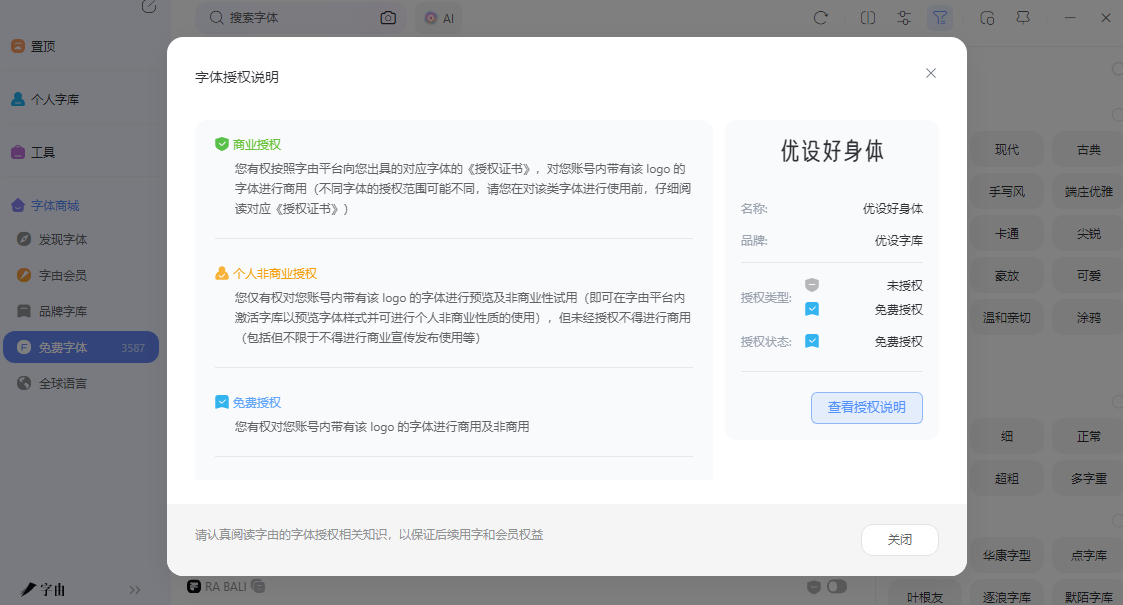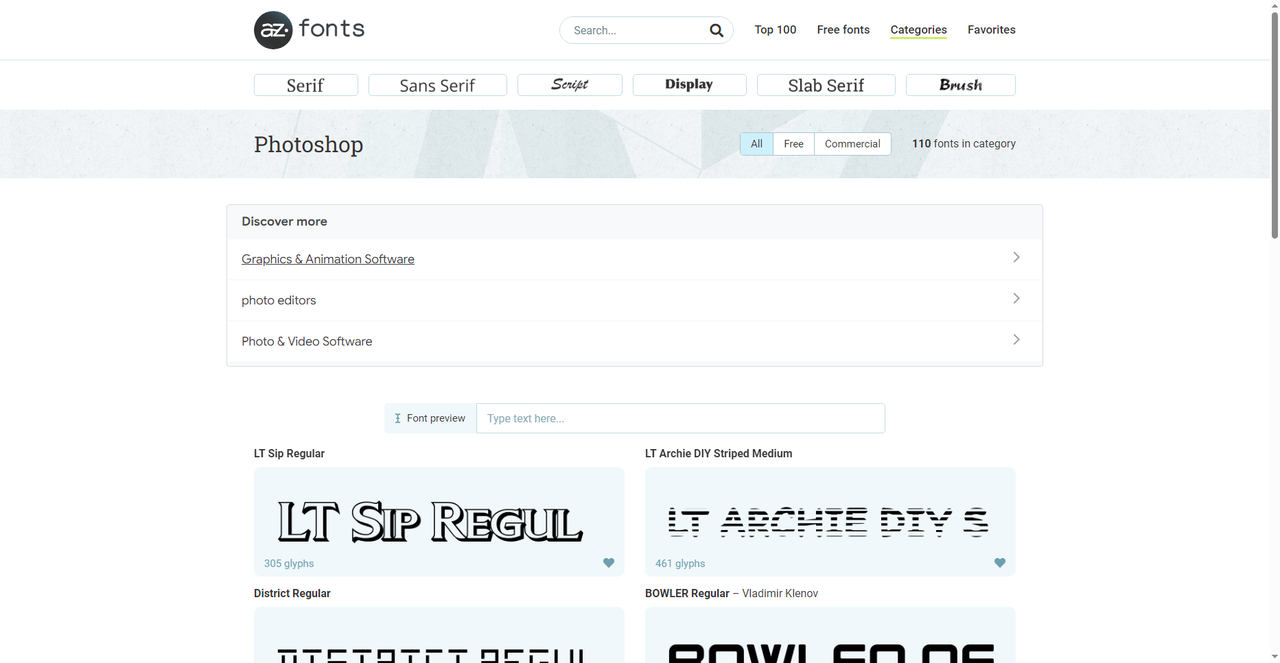
PS英文字体哪里找?这5个网站免费下载又好看
打开Photoshop的字体下拉菜单,你是不是也这样:看到Arial和Times New Roman总觉得太老气;Helvetica的话又不够个性。翻来覆去就那几款系统默认字体,做出来的海报、Logo、封面,总感觉跟别人的差不多。其实不是PS不行,是你的字体库内容太少了。网上有很多专门给设计师准备的英文字体网站,免费、可商用、风格多样,下载后直接装进PS里用。今天我就整理了5 个靠谱的英文字体资源站,从免安装激活到一键下载,覆盖了不同使用习惯。
字由它和其他字体下载站最大的区别是:你不需要下载任何字体文件。打开字由客户端,里面收录了上万款字体,其中英文字体占了很大比重。找到想要的英文字体,点一下“激活”,它立刻出现在PS的字体列表里,不用重启软件,不用打开系统字体文件夹。
字由的筛选功能做得很细。左侧筛选栏里,在“字体语言”下勾选“英文(拉丁)”,所有英文字体会一次性列出来。然后你可以继续按“字体类型”筛选:衬线体、无衬线体、手写体、展示体、等宽体……每种风格下面又有几十到上百款具体字体。
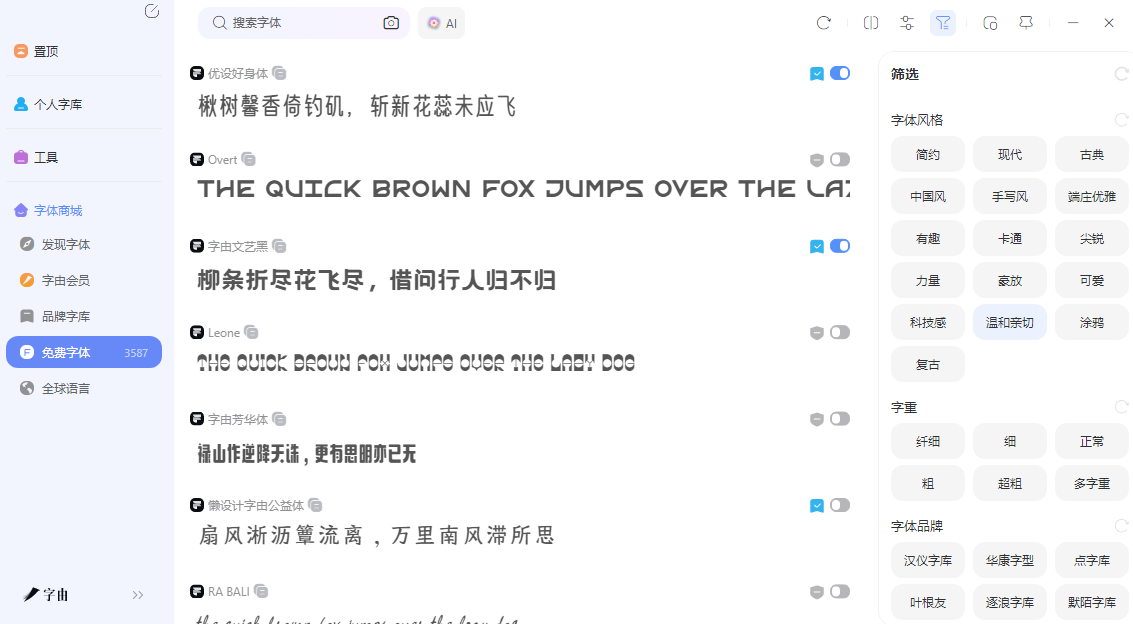
比如你想找一款适合做海报标题的粗体英文字体,勾选“英文”+“展示体”+“免费商用”,系统会把你需要的所有字体列出来,每款都有预览图,输入你自己的文案实时看效果。找到喜欢的,点一下“激活”,打开PS,在字体下拉菜单里就能看到它。因为字由的“激活”机制太适合PS了。不喜欢的点“取消激活”,字体就从PS列表里消失,不占系统空间。
就算换了设备也不用怕,字由的个人云字库可以把你激活过的字体、收藏的字体自动同步到云端。你在公司电脑上激活了一堆英文字体,晚上回家打开笔记本,登录同一个字由账号,PS里那些字体全都在,不用重新找重新激活。而且字由支持Windows和macOS,不管你是用PC还是Mac版PS,字体库始终一致。
2、fonts
第二个网站就叫fonts。这个站有个很实用的功能:它专门做了一个“Photoshop”分类标签。截图显示,在分类筛选里直接有“Photoshop”选项,点进去能看到110款适合在PS中使用的英文字体。为什么这些字体被标记为“Photoshop”?可能是因为它们多为OpenType格式,支持PS的高级排版功能(如连字、替代字符等),或者本身就是设计师在做PS项目时高频使用的款式。这个分类帮PS用户省去了“下载一堆字体然后发现不适合”的试错成本。这个站上的字体授权类型混合,下载前需要看页面标注。但“Photoshop”分类下的字体大多是免费或免费商用的,适合PS用户直接下载安装。
3、FreeFontsVault
第三个网站是FreeFontsVault。这是一个老牌的免费字体资源站,首页展示了最新推荐的免费字体,比如“Grad Theft Auto V”“SKIBIDI”“TOILET”“FF Trixie Font”“Corleone Font”“GTA 6 Logo Font”“Skibidi Toilet Font”等。
比如你要做一个复古风的Logo,点“Vintage”标签;要做海报标题,点“display”或“headline”;要搭配品牌VI,点“elegant font”或“clean font”。每个标签下都有大量免费字体,全部支持免费下载。网站还提供了搜索框,可以按字体名称直接搜。FreeFontsVault上的字体授权大多是免费个人使用,部分标注免费商用。下载前建议看一下字体详情页的说明。如果你是一个喜欢“逛”字体站、按风格翻找的设计师,这个站的标签系统会让你很顺手。
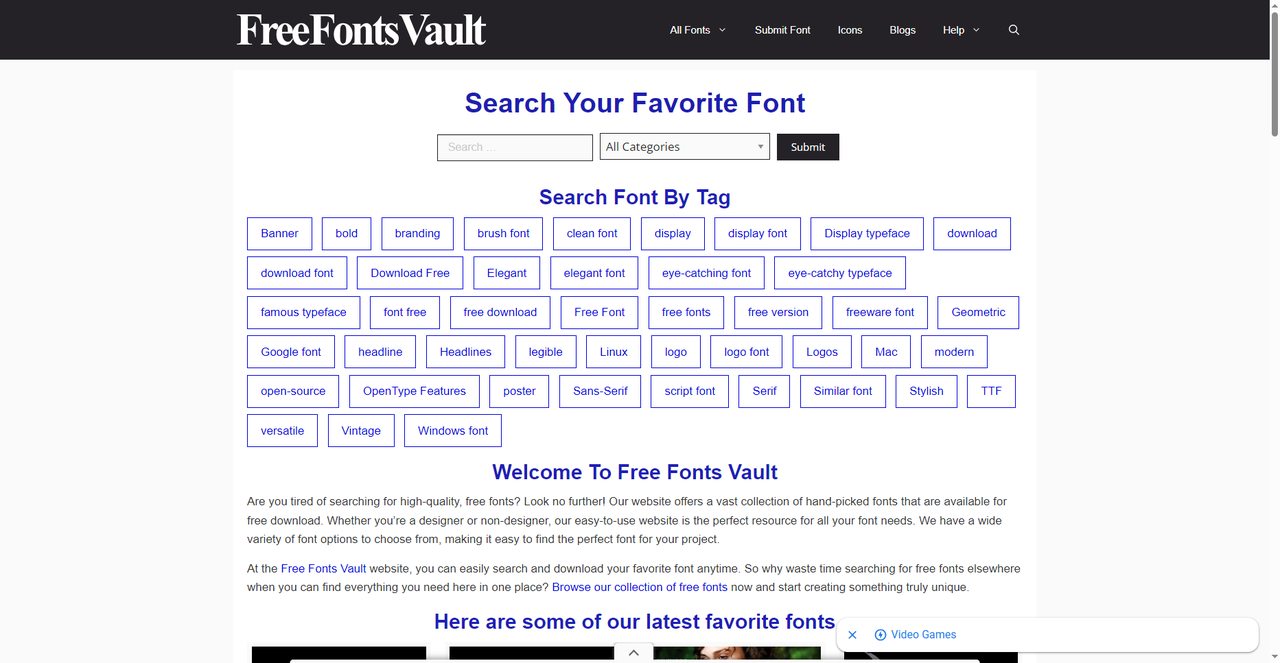
4、fontbolt
第四个网站是fontbolt。这个站的定位很特别——它专门收集电影、游戏、音乐、书籍相关的主题英文字体。如果你正在做一张电影主题的海报,或者要给一款游戏设计Logo,或者想模仿某部经典电影的片名字体,fontbolt是最快的资源站。它收集了大量基于流行文化IP的字体复刻版,比如《侠盗猎车手》字体、《星球大战》字体等。这些字体大多是粉丝复刻的免费版本,适用于个人项目,商用需要谨慎确认授权。fontbolt的字体下载通常直接提供TTF文件,下载后双击安装就能在PS里用。适合做娱乐向、流行文化向的设计项目。
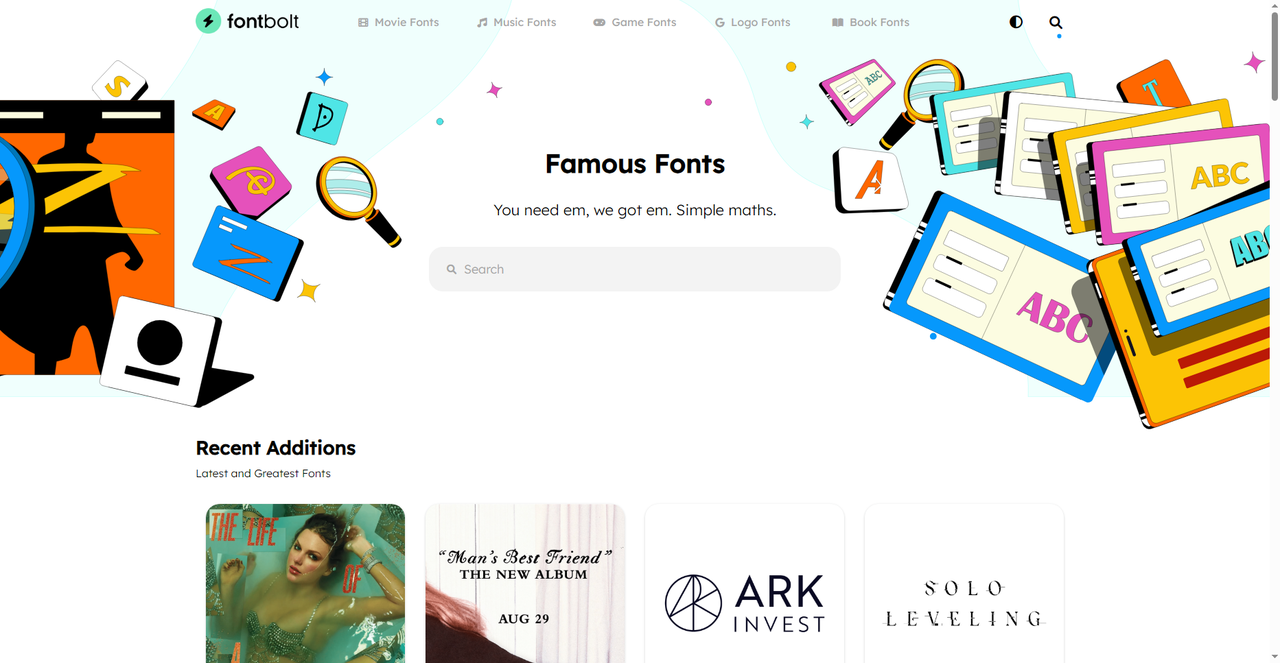
5、Adobe Fonts
第五个工具是Adobe Fonts。它不是独立的网站,而是Adobe Creative Cloud订阅的一部分。只要你订阅了PS、AI等Adobe软件,就可以免费使用Adobe Fonts里的上千款专业字体。Adobe Fonts的优势在于:字体直接同步到你的Adobe软件里。在PS里打开“字体”菜单,点击“从Adobe Fonts添加字体”,浏览网页,点击“激活”字体,它立刻出现在PS的字体列表中,不需要下载、安装。和字由的激活机制类似,但只限于Adobe生态。如果你已经是Creative Cloud用户,Adobe Fonts是你最方便的选择。它收录的字体都是专业字体公司出品,质量极高,且全部授权用于商业项目(只要你的订阅有效)。缺点是非订阅用户无法使用。
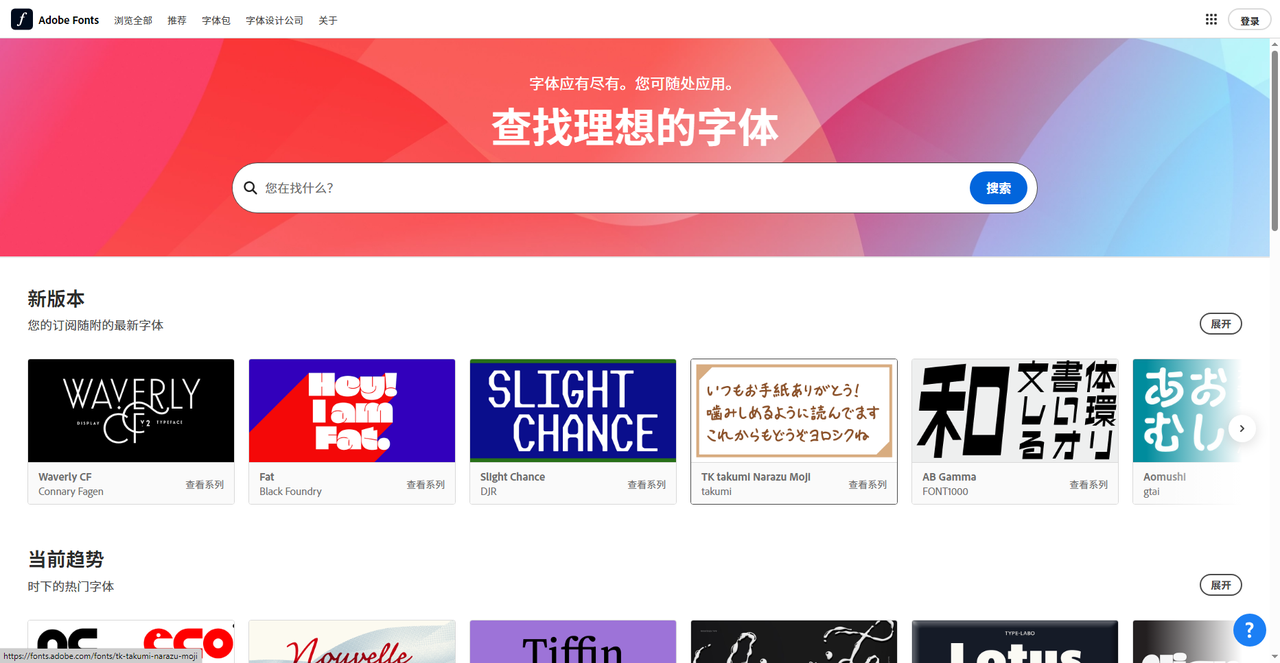
5个英文字体网站,覆盖了不同使用习惯。字由最适合不想折腾下载安装的PS用户,点一下激活就能用,还有免费商用筛选和云字库同步;fonts网站专门做了“Photoshop”分类,110款字体直接对号入座;FreeFontsVault标签系统完善,适合按风格翻找的探索型设计师;fontbolt收录大量电影游戏主题字体,适合娱乐向项目;Adobe Fonts是订阅用户的最优解,字体直接同步到PS。如果感兴趣的话可以直接去试试,相信你会有收获。